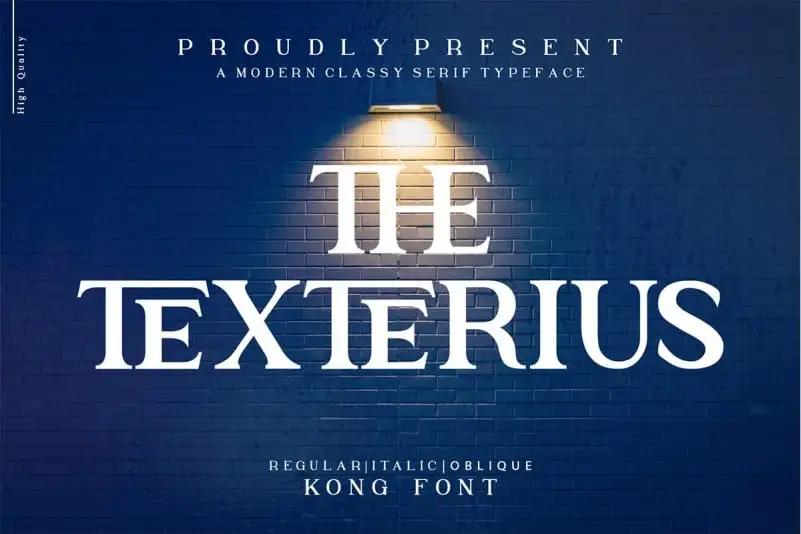
The Texterius Serif Font – Fonte Grátis
The Texterius Serif Font
A fonte “Texterius Serif” foi projetada com objetivo de ser uma tipografia agradável para leitura em telas. Compondo caracteres maiúsculos, alternativas, ligaduras, números de 0 a 9 e uma variedade de pontuação e símbolos (em formato OTF, TTF e WOFF), esta fonte oferece suporte multilíngue. Suas capacidades incluem trabalhar perfeitamente em projetos criativos como logotipos, camisas / vestuário, selos, convites, embalagens, headlines, panfletos, revistas e cartões de agradecimento para casamentos. Esta fonte é uma opção ideal para quem busca uma tipografia suave e moderna que se destaca em qualquer projeto gráfico, sem comprometer a legibilidade.